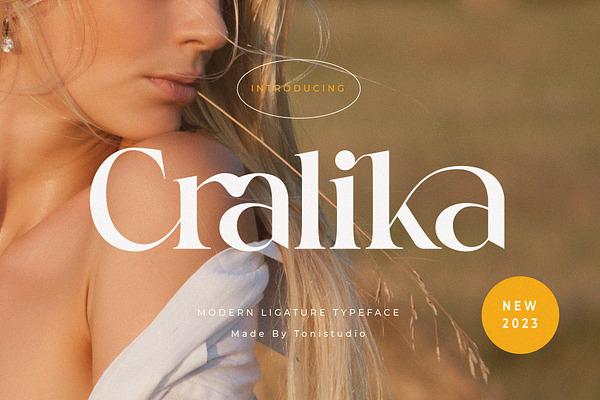
Cralika 现代连笔衬线字体
Cralika Modern Ligature Serif
画面展示了一位金发女性的侧脸,背景为温暖的自然光,整体色调柔和,充满优雅与现代感。Cralika 是一款现代连笔衬线字体,具有流畅的笔画和精致的连笔设计,适合用于标题、海报、品牌标志和包装设计,能为作品增添高级感与艺术气息。